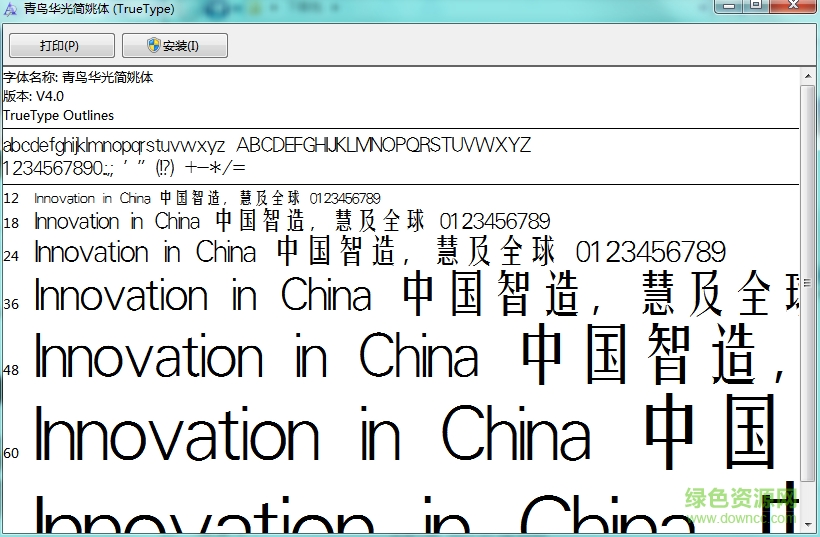
青鳥華光簡姚體是一款細(xì)線字體,字跡筆直嚴(yán)謹(jǐn),有著清新的閱讀觀感和較好的說明作用,如果您喜歡本款字體,那就來綠色資源網(wǎng)免費(fèi)下載吧!
青鳥華光簡姚體是一款字跡清明中和的姚體字體,以細(xì)長大方為主,采用宋體欣長娟秀的精髓,讓平面設(shè)計、名片設(shè)計、海報印刷等更顯時尚感。
字體雋秀工整,結(jié)構(gòu)狹長,字間距較大,排印清晰,整齊劃一,適用于書籍、報刊、雜志的標(biāo)題字。姚體在宋體的基本骨架上融合了黑體和仿宋體的特點(diǎn),采取更為簡潔概括的筆畫形態(tài),整體字型清秀瘦長、端莊正氣,呈現(xiàn)出非常鮮明的“美術(shù)字”風(fēng)格。